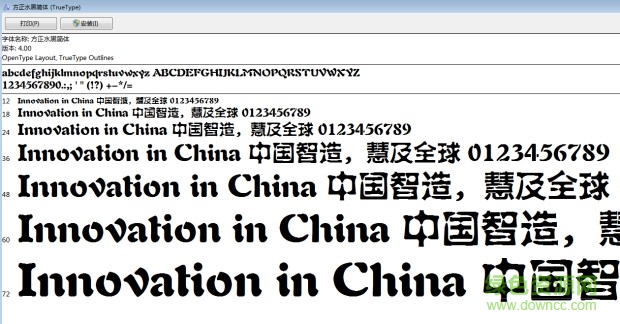
fzshhjw gb1 0字體是方正字體中的一款免費字體,這款字體中文名又叫方正水黑簡體,字形簡單漂亮,可以用來設計廣告、印刷品等等。感興趣的朋友趕緊來綠色資源網(wǎng)下載吧!
fzshhjw gb1 0方正水黑簡體字形效果漂亮,字體大氣工整。是一款非常漂亮的簡體字體,,寫法工整美觀,飄逸大方。